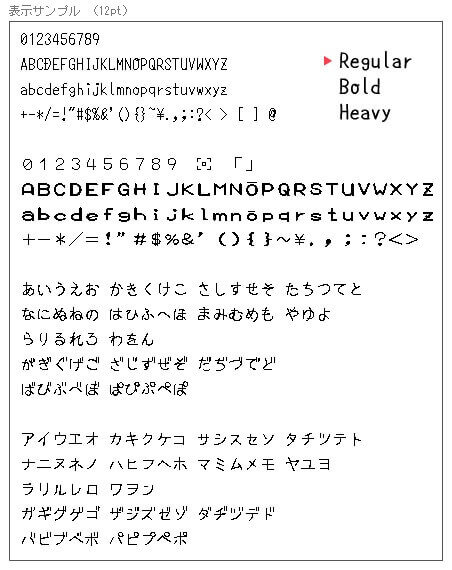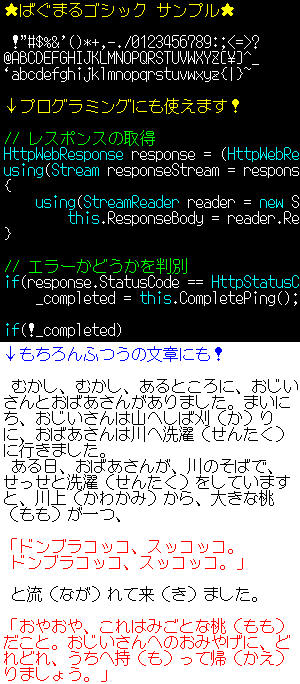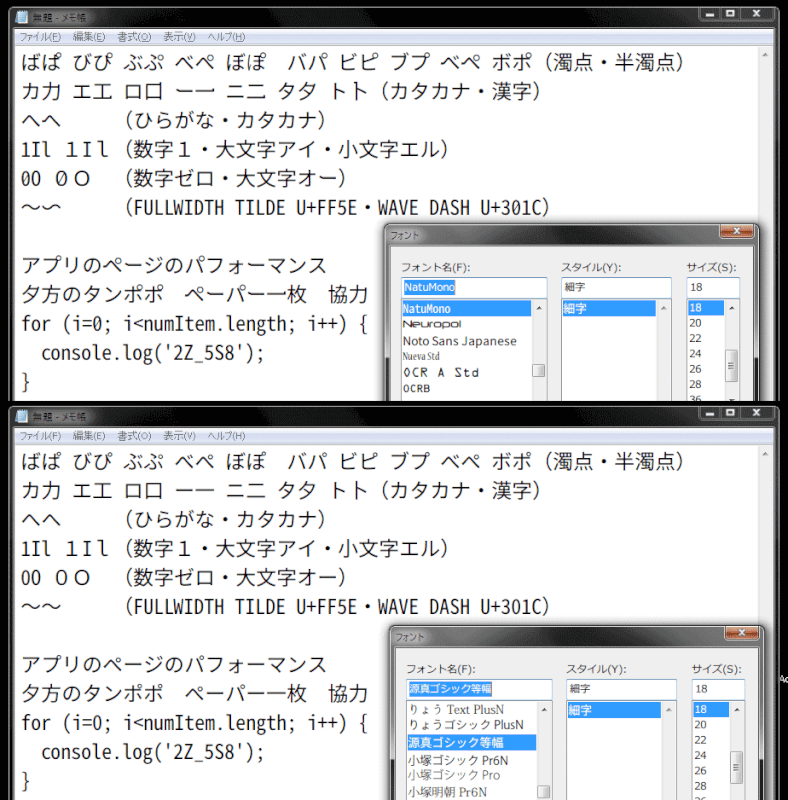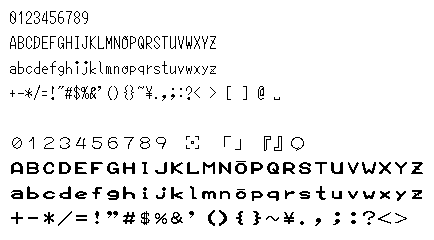
プログラミングにおすすめ!コーディング用フォント6選
多くの文字が画面に表示されているプログラミング時にストレスなくコーディングするためには視認性が高いフォントを選ぶことが大切です。今回は、インストールするだけでプログラミングする時に見やすいフォントを6つご紹介します。
NatuMono
源真ゴシック (げんしんゴシック)の等幅 Regularを改変したフォント。
ばぐまるゴシック
画面表示用のビットマップフォント。コーディングで使えるように、0(ゼロ)と O(オー)などが区別できるように作られています。
ゆたぽん(コーディング)バックスラッシュ
コーディングする時に見やすいフォント。「半角¥」が「半角\」に変更しています。
ゆたぽん(コーディング)+BMP
コーディングする時に見やすいフォント。英数字だけビットマップフォントを含んでいます。
ゆたぽん(コーディング)+BMP+spc
上記の「ゆたぽん(コーディング)+BMP」の半角スペースを記号にしたバージョン。
源暎ゴシックM
MS ゴシックなどと同じように一部の英数字が半角等幅、それ以外が全角等幅になっているフォント。